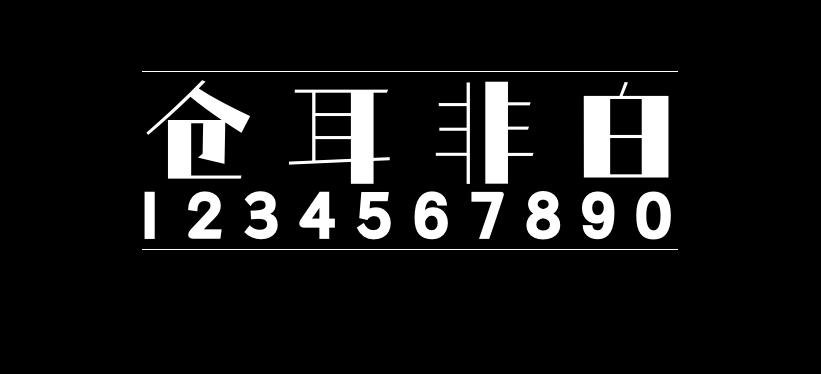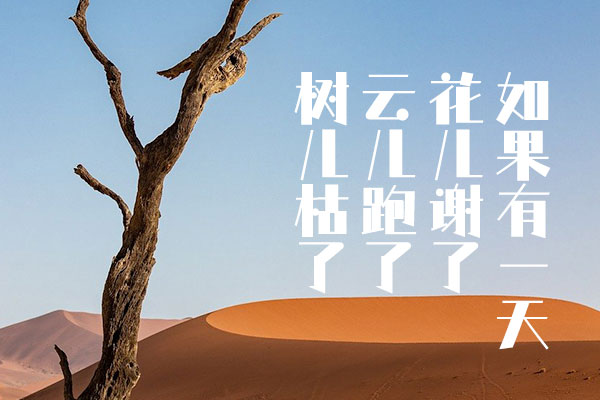
仓耳非白
仓耳非白(TsangerFeiBai)是仓耳字库创作的一款免费字体,是一款粗细对比明显、风格强烈、拥有5个字重的家族字体,结构方整,笔形简洁、利落,带有明显区别于其他字体的风格。
设计时,除了加粗笔形强调“黑”,也增加了部分细线强调“白”,字形转折处均做直角处理,撇捺同样以直线表现,最终成字呈现强烈的粗细对比。点的部分改为圆形,方圆结合,整体结构更加柔和。